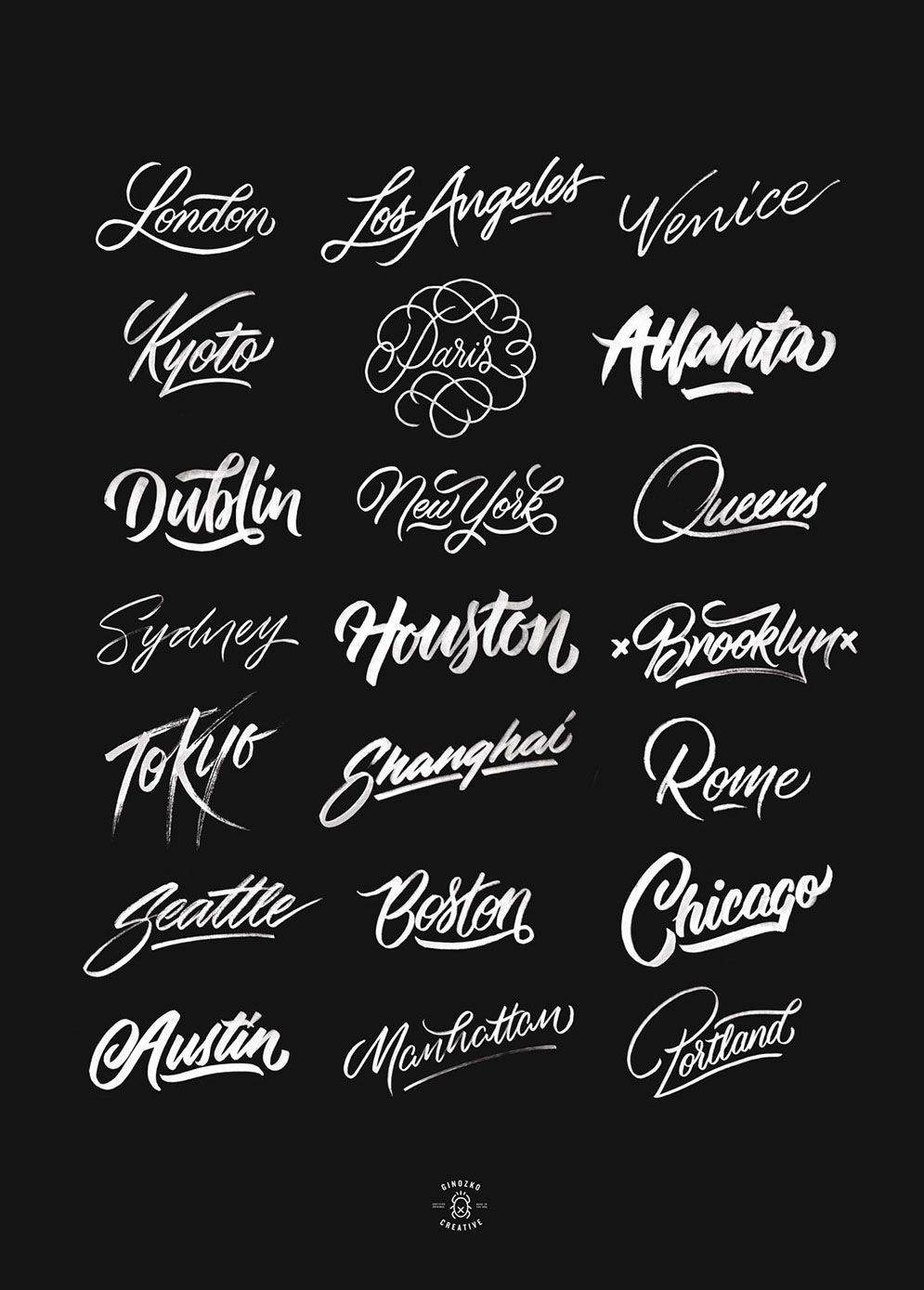
Тату шрифты онлайн | Более 1000 видов для скачивания и печати
Одним из самых распространенных стилей тату-индустрии является нанесение какого-либо текста для выполнения татуировки в итоге. Выбор текста – вопрос непростой, но еще более сложным будет выбор самого шрифта. Учитывая целое море вариантов, а также индивидуальный подход мастера к каждому, можно долго рассуждать о конкретных типах тату.
Стиль шрифта
Как выбрать шрифт для тату? Первым делом, если Вы определились с текстом, нужно подобрать соответствующее оформление. Кроме того, стоит учесть стиль самого клиента, что подойдет под стиль его хобби, работы, жизненных ценностей. Исходя из множества деталей можно определить для себя наилучший вариант.
Размер шрифта
Чтобы определиться с размером шрифта нужно определить точное размещение текста. Расположив его, можно представить другие варианты размеров – ширины и длины каждой буквы. Текст может состоять как со строчных буков, так и начинаться с заглавной, выделяя имя или город, страну.
Цвет надписи
Если Вы рассмотрели тату шрифты и определились с вариантом, а также уверены в тематике надписи, можно рассмотреть палитру цветов. Возможно, наилучшим вариантом будет черно-белая татуировка или же актуальнее будет сделать тату в ярких цветах. Можно сделать несколько цветов, комбинируя их:
- Сделать яркую обводку.
- Добавить цветную тень.
- Заполнение букв может быть с цветовыми переходами.
Посоветуйтесь по поводу выбора шрифта и цветов, а также оттенков и стиля нанесения с нашими мастерами, выберите наилучший вариант и исполните его у татуировщика, который Вам его посоветовал. Это оптимальный вариант для получения желаемого результата. Выбранные на сайте шрифты онлайн отобраны как наилучшие и наиболее удачные для практически любых мест нанесения. Стиль самого тату может быть как минимализм, так и готика или графика. Вы сами выбираете наилучший стиль для своего тату, однако совет мастера всегда будет полезен. Рассмотрите тату шрифты у нас, подумайте об оформлении, выберите несколько вариантов и продумайте заранее все детали.
Язык надписи
Немаловажным фактором является выбранный язык для татуировки. Исходя из выбора, нужно прикинуть шрифт, так как не каждый из них хорошо смотрится на том или другом языке.
Для понимания онлайн пропишите надпись, которую собираетесь набивать, чтобы рассмотреть все преимущества и недостатки того или другого шрифта.
Популярные места для татуировки
Место для тату – выбор клиента, однако устоялись популярные места для нанесения шрифтов. Такими местами можно считать предплечья рук, ноги, менее часто встречаются надписи на руках, спине. Многие клиенты рассматривают тату шрифты для выполнения на груди, вроде порядкового номера или имени любимого человека.
Предпочтения в шрифтах
Сразу можно представить, что девушки больше любят утонченность, изысканность линий, тонкие и легкие шрифты. Если говорить о мужском поле, то предпочтение отдается более крупным, жирным и наляпистым надписям, большинство из которых имеют обводку, возможно цветную. Однако, эти стандарты не всегда подходят под наших клиентов, учитывая, что большинство из них – люди с яркой внешностью и хорошим вкусом.
Разборчивость
На первый взгляд может показаться, что разборчивость и читаемость — это одно и то же, но это не так. Разборчивость относится к дизайну шрифта, например, по ширине штрихов, независимо от того, есть ли у него засечки, наличие новых элементов дизайна шрифта и т. Д. Легко отличить одну букву от другой в разборчивом шрифте.Например, декоративные гарнитуры плохо читаются, потому что они в первую очередь предназначены для того, чтобы их можно было увидеть с первого взгляда, а не читать подробно. И наоборот, гарнитуры, предназначенные для романов или газет, имеют очень высокую разборчивость. Вам необходимо разработать определенную общую читаемость на основе функции текста.